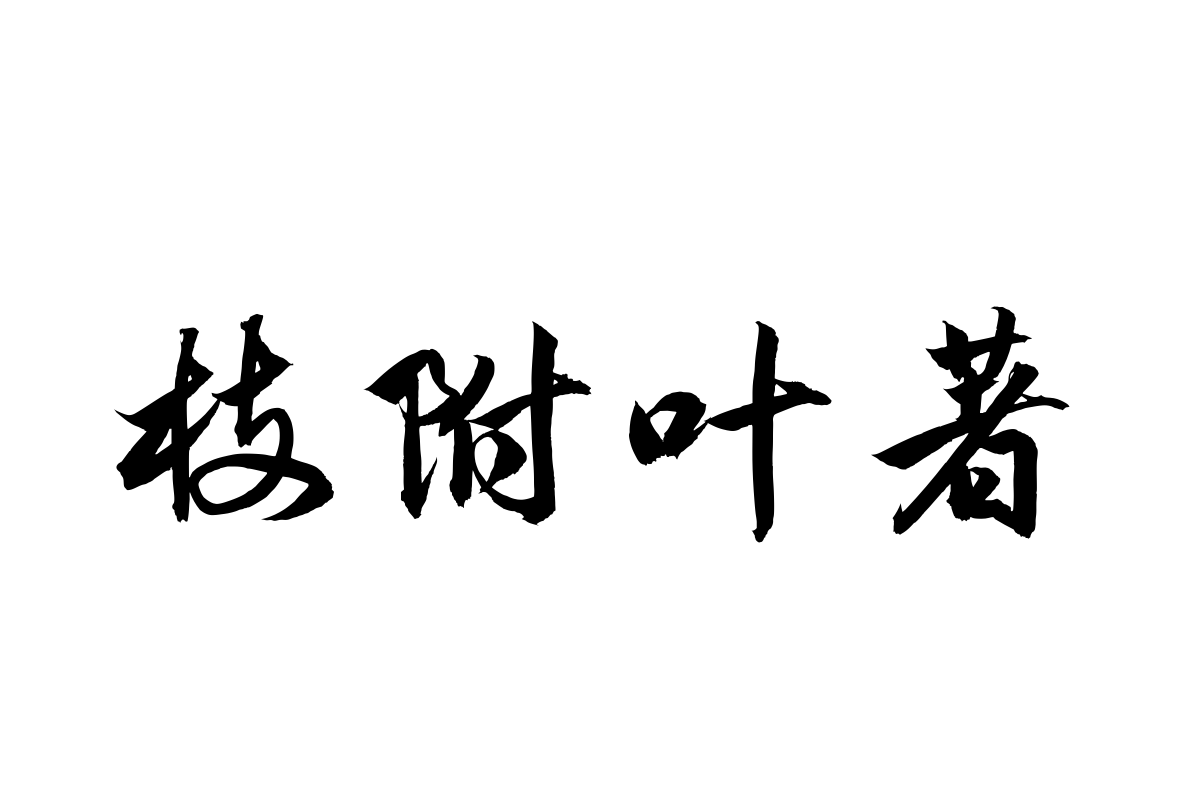
汉仪状元行是一款具有中国传统特色的书法字体,其特点是笔画流畅、结构严谨、风格独特。该字体适用于各类书籍、报纸、杂志等出版物,以及网页设计、广告宣传、包装设计等领域。
汉仪状元行的特点如下:
1. 字形规整:汉仪状元行的字形结构严谨,线条流畅,给人以庄重、大气的感觉。
2. 笔画丰富:该字体的笔画丰富多样,既有传统的楷书笔画,又有隶书、篆书等多种风格,使得字体更加生动有趣。
3. 风格独特:汉仪状元行的字形结构与常见的楷书、隶书、篆书等字体有所不同,具有一定的辨识度和艺术价值。
4. 适应性强:汉仪状元行适用于多种应用场景,无论是用于印刷出版还是网络传播,都能展现出良好的视觉效果。
5. 易于使用:汉仪状元行的设计简洁明了,易于学习和应用,适合广大设计师和用户使用。